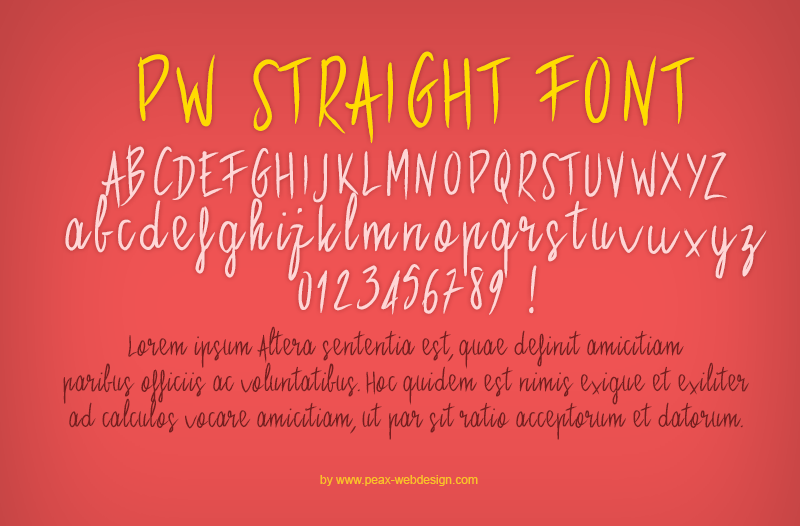
A fonte PW Straight Font é uma sugestão perfeita para aqueles que buscam um visual despojado e moderno. Seu estilo clean e direto faz dela uma escolha ideal para sites pessoais, blogs ou qualquer projeto onde você quer transmitir um tom leve e descontraído. Desenvolvida pelo designer Hamilton, esta fonte é especialmente adequada para uso em design gráfico casual ou quando você está procurando por uma opção prática que não compromete a estética. A fonte oferece uma experiência de usar simples e intuitiva, garantindo um texto fácil de ler, mesmo em pequenas medidas. É importante mencionar que PW Straight Font é do tipo de software de domínio público conhecido como “Donationware”. Isto significa que você pode usá-la gratuitamente no seu site pessoal ou para projetos de interesse pessoal. No entanto, se estiver planejando usar a fonte em um projeto comercial ou monetário, é necessário fazer uma doação através da página dedicada de Hamilton, tanto para apoiar o trabalho dele quanto para garantir que ele continue criando novas e inspiradoras fontes. Já visitou o site do designer no Facebook (www.facebook.com/pages/Peax-Webdesign/358656367486305) ou Google (+plus.google.com/103595703505477716588)? Aqui você encontrará notícias sobre novas fontes e outros recursos do designer. Não perca tempo, explore a variedade de opções de design que Hamilton oferece.